فونت نارنگی با نام «براش» در دومین هفته تایپ تهران حضور داشت و به عنوان فونت برگزیده این رویداد انتخاب شد.
همزمان با انتشار فونت نارنگی پس از دو سال وقفه، گفتوگویی با طراح فونت، کریم شاهین انجام دادیم. در این مصاحبه، او از نخستین مواجههاش با حروف در کلاس چهارم ابتدایی، شکلگیری فونت براش، دلایل تغییر نام آن به نارنگی و برنامهاش برای انتشار فونت جدید میگوید.
چه شد که به دنیای طراحی حروف وارد شدید؟
وقتی بچه بودم، مجبور بودم ساعتهای مشخصی رو توی اتاق بمونم و درس بخونم. حوصلهی درس خوندن نداشتم، کلمات داخل کتاب رو به شکلهای مختلف مینوشتم تا زمان درس خوندن بگذره. این کار تبدیل به عادتی شد که تا امروز هم ادامه داره. یه جور سرگرمی بود ولی در واقع داشتم مشق میکردم و اتود میزدم.
وقتی برادرم این علاقه رو دید، کلاس خوشنویسی ثبتنامم کرد. اون موقع چهارم ابتدایی بودم. توی کلاس هفتم، مدرک عالی خوشنویسی رو دریافت کردم ولی دیگه مقطع ممتاز رو ادامه ندادم. شهر ما ایلام هنرستان نداشت؛ توی دبیرستان رشتهی ریاضی رفتم و بعد در مقطع لیسانس شیمی خوندم. ولی میدونستم که بالاخره یه روزی گرافیک میخونم.
با لیسانس شیمی فونت طراحی کردید!؟
خیر. سال ۹۶ در کنکور هنر شرکت کردم و گرافیک دانشگاه تهران قبول شدم. در کلاس طراحی حروف استاد جباری، اولین فونتم رو طراحی کردم. بعدتر برای پایاننامه، موضوع طراحی قلم فارسی رو انتخاب کردم که حاصل اون دو فونت گوزن و براش بود که هر دو به عنوان فونت برگزیده در هفته تایپ تهران انتخاب شدند.
ایده اولیه طراحی براش از کجا شکل گرفت؟
اتودهای اولیه حروف فونت براش با قلم موی ژاپنی زده شدن و سعی داشتم نرمی و روانی نوشتار دستنویس رو در حروف این فونت حفظ کنم. به همین دلیل نام براش رو برای اون انتخاب کردم.
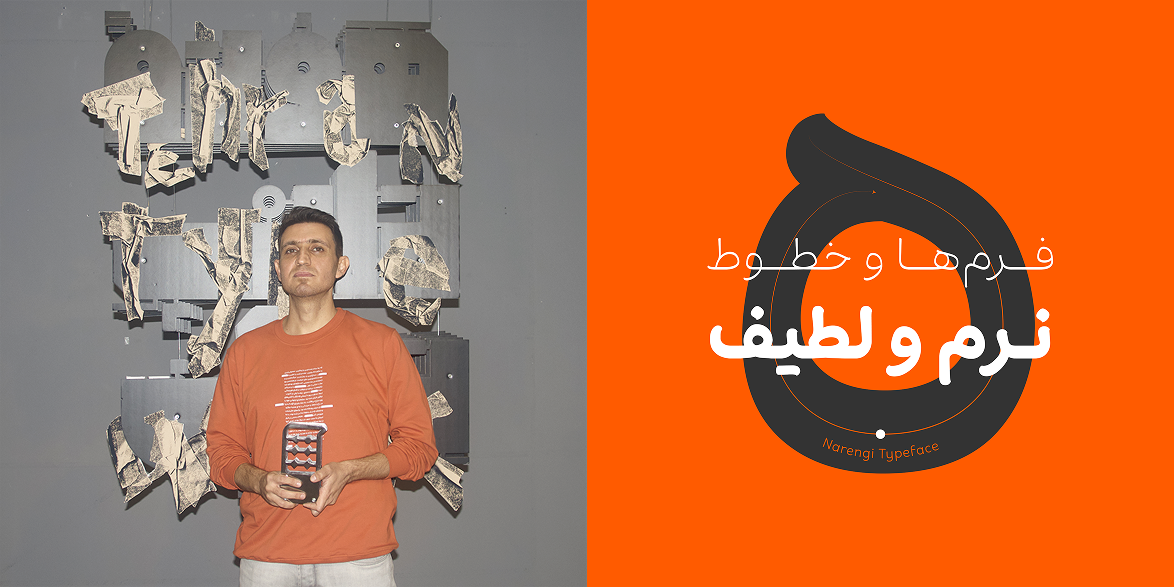
چرا انتشار فونت دو سال طول کشید و چرا نام براش را تغییر دادید؟
به عنوان اولین کار، کیفیت و سلامت فونت برام خیلی مهم بود. از طرفی میخواستم فرایند ساخت فونت(دولوپ) رو از صفر تا صد خودم انجام بدم.
دوست نداشتم فونت با نام براش منتشر بشه چون در طول فرایند تولید، فونت از اون ایده اولیه خیلی جلوتر رفته بود و صرفا یک فونت با فرمهایی شبیه به قلم مو نبود. از طرفی نامهای فارسی رو بیشتر ترجیح میدادم. به همین دلیل تصمیم گرفتم اسم فونت رو عوض کنم.
ایده نام «نارنگی» از کجا آمد؟
اول اینکه به نظرم این فونت، فونتی نرم با فرمهای روان و بامزه است و به نظر خودم رنگش نارنجیه. مورد دوم اینکه دنبال اسمی بودم که هویت مشخص و نمود بیرونی و فیزیکی داشته باشه تا در ذهن مخاطب بمونه.
چند جمله از ویژگیهای فونت نارنگی؟
فونت نارنگی سعی میکنه متناسب با فضا، شخصیتی منعطف داشته باشه. در وزنهای پایین، کم سر و صدا و منظمه تا فرایند روان خوانی رو مختل نکنه. ولی در وزنهای بالاتر سعی داره با صدای بلند و رسا شخصیت خودش رو بیان کنه.
نارنگی همچنین در بعضی حروف دارای یک سری کشیدگی عرضیه که هدف این کار انعکاس ساختار آوایی زبان فارسی در ساختار فونته. بیشتر فونتهای فارسی موجود، هندسی هستند. نارنگی تلاش کرده بخشی از کمبود فونتهای با فرمهای منحنیتر رو پر کنه.
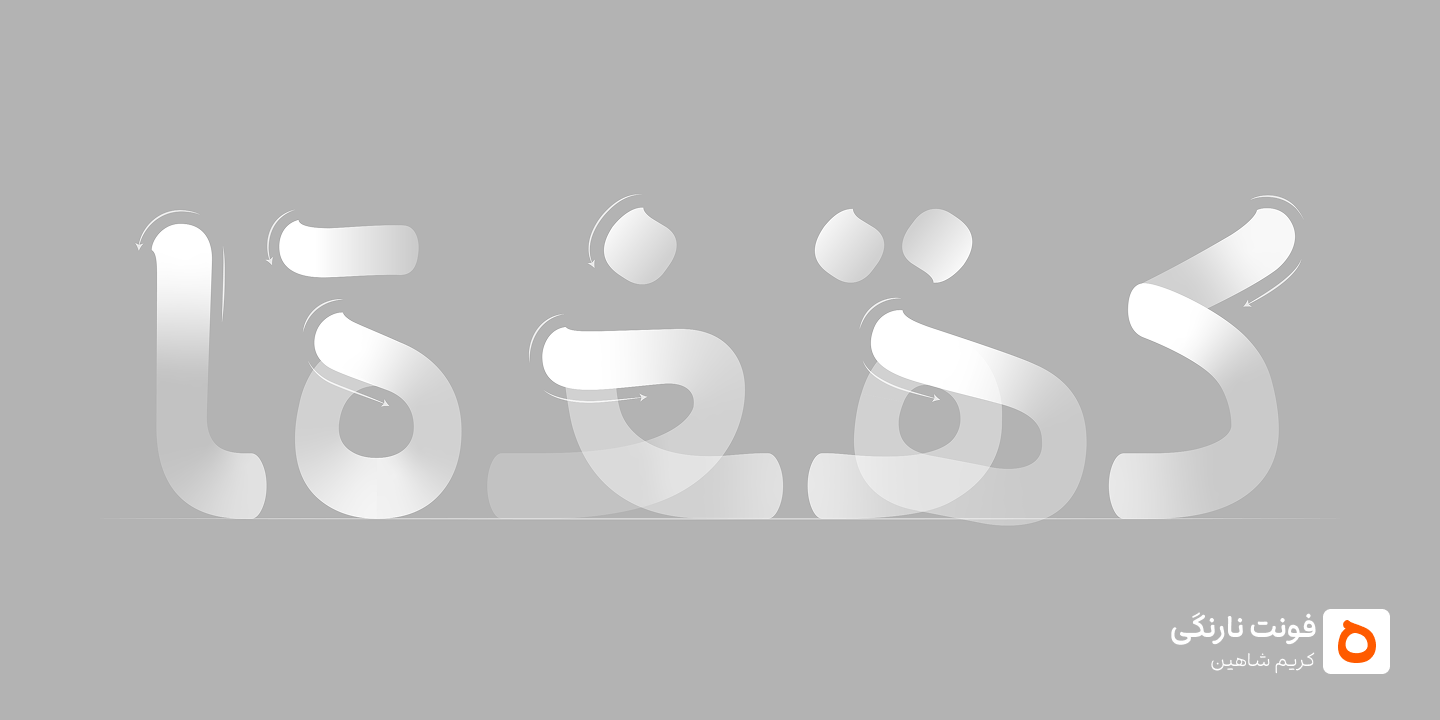
فونتهای مورد علاقهتان از میان آثار دیگر طراحان تایپ کدامند؟
خیلی از فونتها رو دوست دارم و انتخاب از بینشون سخته. فونتهای پتک، هستی و ابر رو خیلی دوست دارم. به نظرم در فونتهای اختصاصی، علی بابا یه شاهکاره و هر بار از دیدنش لذت میبرم.
سوال پایانی؛ به جز نارنگی، یک فونت برگزیده دیگر هم دارید، چه زمانی منتشر میشود؟
امیدوارم بتونم فونت گوزن رو در سه ماه آینده منتشر کنم چون مشتاقانه میخوام برم سراغ فونتها و تجربههای بعدی.